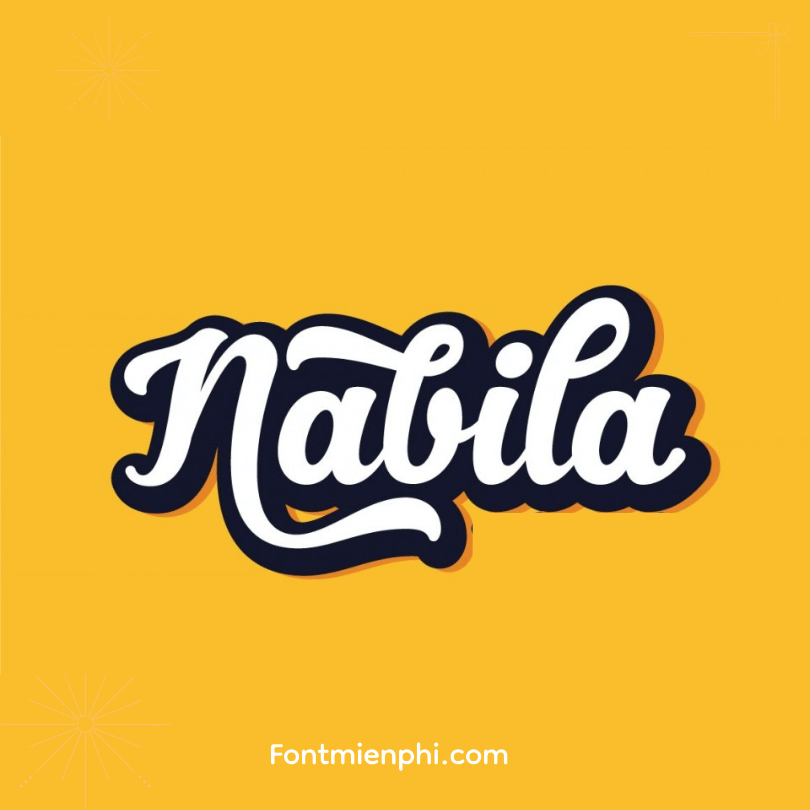
Hướng Dẫn Việt Hóa Font iCiel Nabila
iCiel Nabila là font chữ nghệ thuật sang trọng, thích hợp cho thiết kế thời trang, logo và nhận diện thương hiệu. Để sử dụng font này cho tiếng Việt, bạn có thể thực hiện các bước sau: